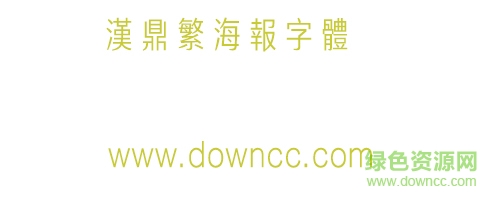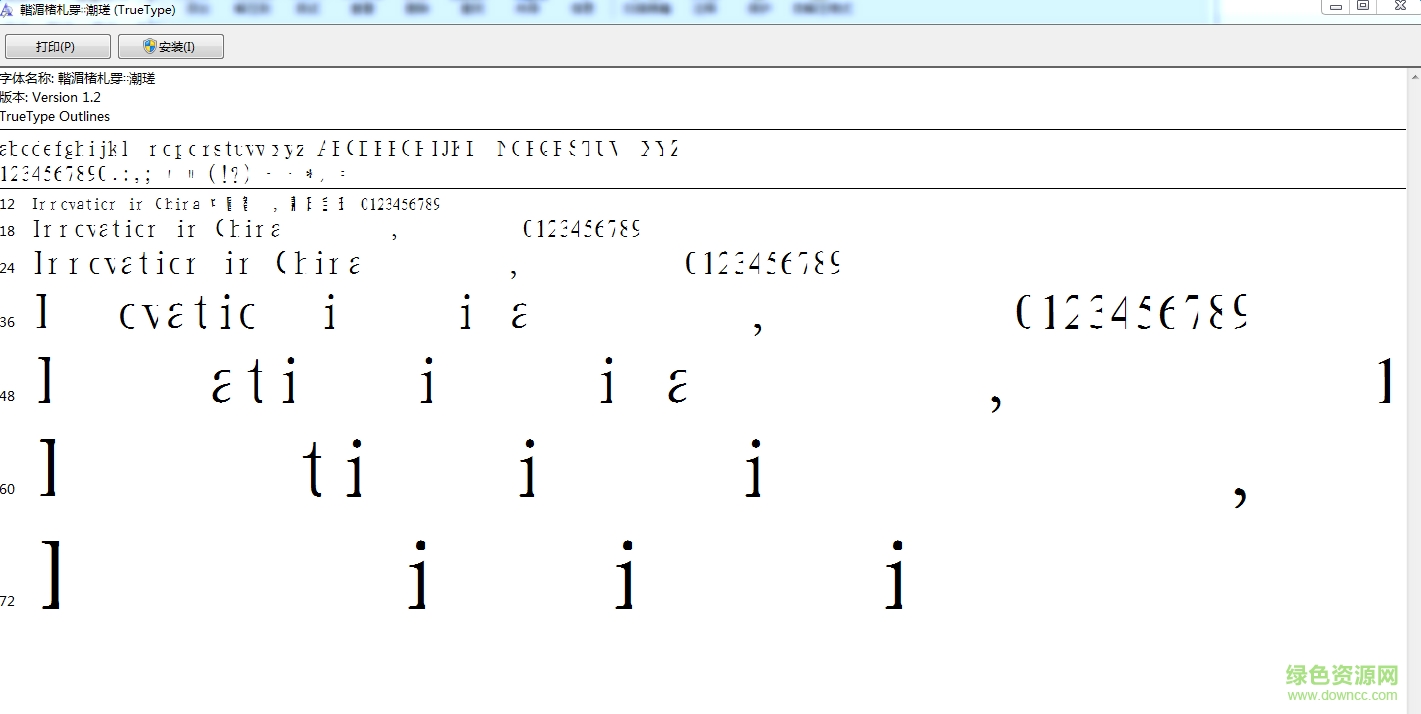
漢鼎繁海報字體是一款漢鼎海報類繁體字體軟件,繁體字給人非常古老的感覺,深受廣大書法家的喜愛,適用于海報等字體需求,還有更多好看字體盡情期待,歡迎到綠色資源網(wǎng)下載體驗!
用于海報設(shè)計方面的字體,字體工整美觀,可用于出版印刷字體、廣告設(shè)計字體、網(wǎng)頁設(shè)計字體、包裝設(shè)計字體、 屏幕顯示字體
漢鼎繁海報是一款海報類繁體字體,字體效果比較繁瑣,喜歡繁體字的朋友可以下載使用看看效果如何。